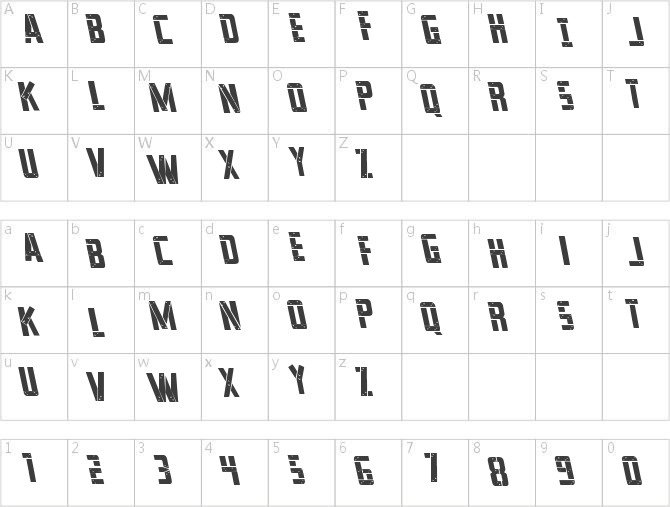
Frank-n-Plank Leftalic
Frank-n-Plank Leftalic介绍
Frank-n-Plank Leftalic字体字库是一款让人赏心悦目、百看不厌的英文字体,适合各类广告和产品包装设计应用,字体大小0.09MB,格式为ttf字体,上传用户是邹湾湾湾湾,作者/版权方为未知